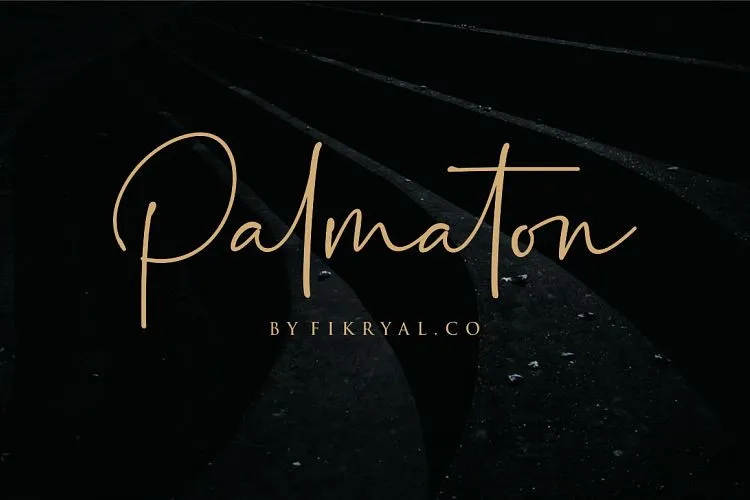
Palmaton Handwritten Font – Download Grátis
Aqui está uma descrição envolvente e natural para a página de download da fonte ‘Palmaton Handwritten Font’ em português do Brasil: Palmaton é uma fonte escrita à mão, perfeita para criar designs com um toque autêntico. Suave e realista, ela traz vida aos seus projetos digitais, proporcionando o selo de confiabilidade que você precisa. Esta fonte foi desenvolvida por m@graphics em colaboração com Fikryal, combinando modernidade e estilismo moderno. Seja para criar um logotipo atraente ou uma identidade visual consistente, para embalar uma mensagem elegante ou fazer o design de uma publicidade chamativa. Com Palmaton, você pode personalizar seus projetos em diversos formatos como convites, títulos, designs de casamento, posts nas redes sociais, anúncios e até mesmo elementos que adicionam um toque único a sua marca. É perfeita para criar uma identidade visual coesa, oferecendo ao seu produto ou serviço o brilho necessário para destacar. Nada como a autenticidade de uma escrita à mão para reforçar a personalidade de suas criações digitais. Com Palmaton Handwritten Font, você terá todas as ferramentas necessárias para criar designs vibrantes e criativos que sejam capazes de capturar a atenção do seu público-alvo. Descubra o poder da autenticidade em cada letra com Palmaton, uma fonte escrita à mão perfeitamente adaptada ao mundo digital.
Designer: m@graphics